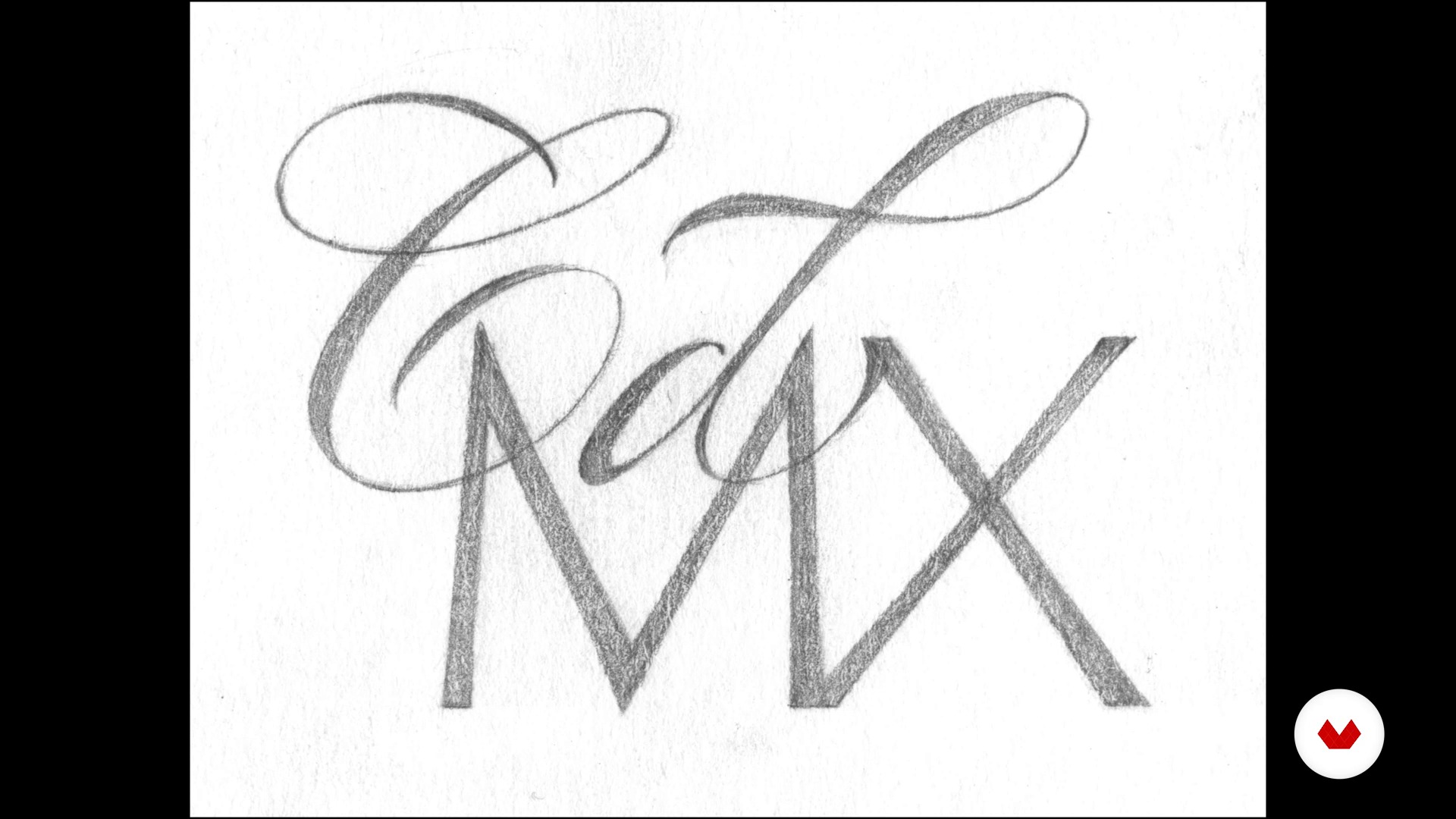
Design de monogramas com estilo
Como misturar tipografia com caligrafia
Um curso de GM Meave , Designer, Ilustrador, Calígrafo e Tipógrafo
Sobre a videoaula: Como misturar tipografia com caligrafia
Visão geral
“Você aprenderá métodos para misturar formas tipográficas com caligráficos para criar tensão e efeito em um logotipo ou monograma.”
Nesta videoaula, GM Meave aborda o tópico: Como misturar tipografia com caligrafia,que faz parte do curso online da Domestika: Design de monogramas com estilo. Aprenda a utilizar a caligrafia e o lettering para criar monogramas dinâmicos e engenhosos.
“Nesta lição, vamos abordar o tema das misturas Como havíamos falado, temos linguagens tipográficas, e estilos caligráficos. Estes podem ser misturados caligrafia com caligrafia em estilos diferentes, ou entre idiomas, de um tipo tipográfico com estilos caligráficos, misture tipografia com caligrafia. Vamos começar com alguns casos, existem inúmeras possibilidades. Mas aqui tenho cinco casos muito específicos que gostaria compartilhar com você. Primeiro, vamos abordar um que é bastante óbvio. Que é a combinação de Serif, com San Serif. Formas de letras com patins e sem patins. Costumam ser m...”